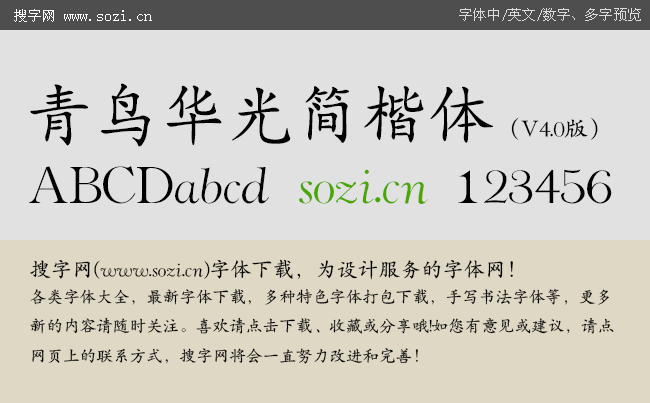
青鳥(niǎo)華光簡(jiǎn)楷體
搜字網(wǎng)提供一款青鳥(niǎo)華光簡(jiǎn)楷體中文字體下載,青鳥(niǎo)華光簡(jiǎn)楷體是一款簡(jiǎn)潔端正的中文字體,該字體形體方正,筆畫(huà)平直,可用于報(bào)刊雜志排版,也適用于平面廣告,圖書(shū)印刷等廣告設(shè)計(jì)場(chǎng)合使用。